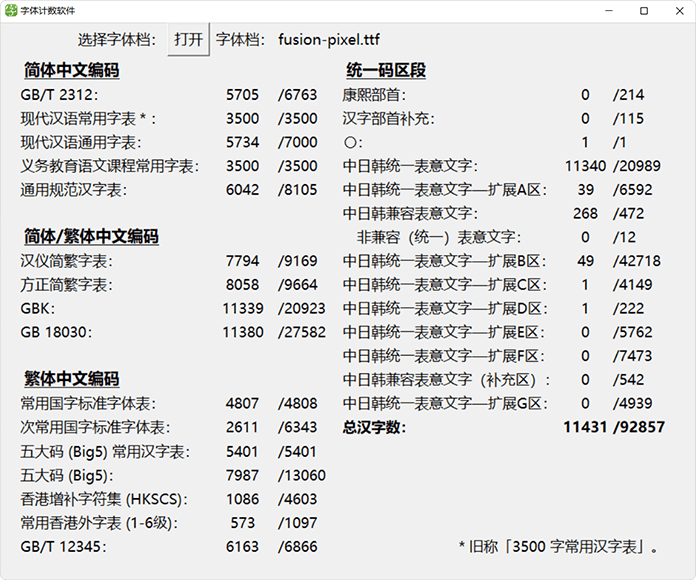
缝合怪像素字体:使用多个第三方像素字体合并而成 免费商用
字体作者:狼人小林 (中国大陆) 字体字重:3个
开源像素字体。支持 8、10 和 12 像素。
该项目为 「方舟像素字体」 可用前的过渡解决方案。使用多个像素字体合并而成,因此以「缝合」命名。
Logo 捏他自 《游戏王》 中的 「融合」 魔法卡卡图。
这个项目提供了从提取字模,合并字形到构建字体所需要的完整程序。
这字体在 7 月 19 日又有更新,不过依然没改动解、底、低、抵、零、滑、个别骨字旁的字形结构,点。
有点震惊的是这么多汉字量却没有「沭」「禸」字,点。
解、滑还是日本字形
这个 12px 版看着不错。